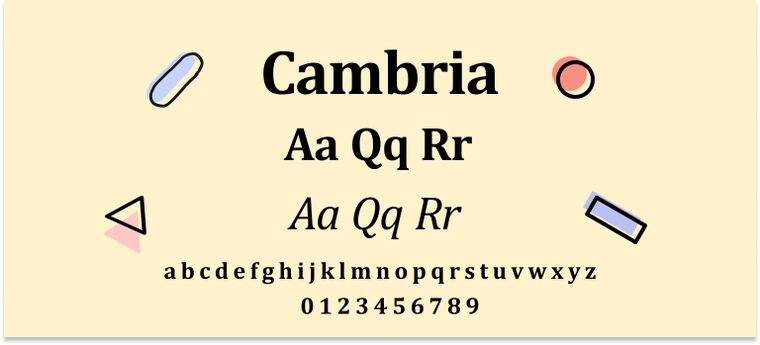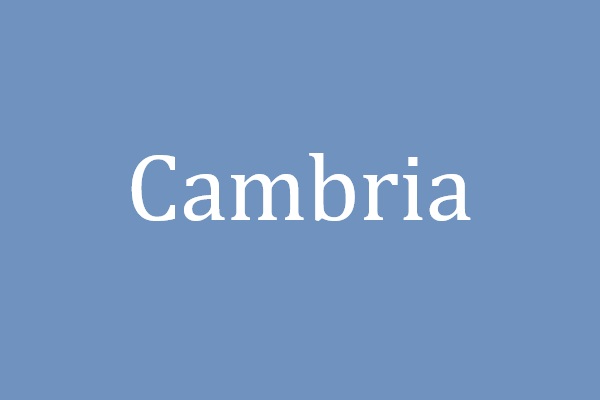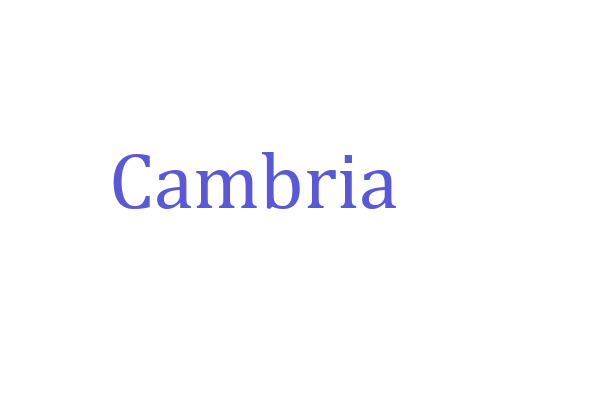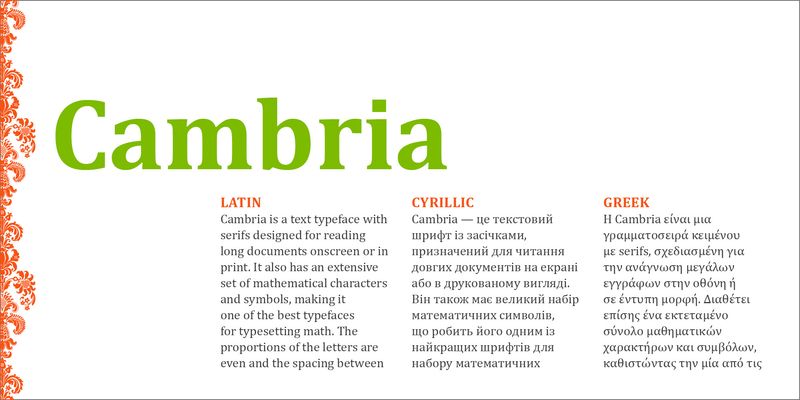
Cambria là bộ phông chữ có chân được thiết kế đặc thù nhằm duy trì khả năng hiển thị rõ nét trên màn hình máy tính và các bản in kỹ thuật. Với cấu trúc chữ vững chãi và độ tương phản vừa phải, việc sử dụng font Cambria Việt hóa mang lại vẻ ngoài trang trọng, tin cậy cho các văn bản thuyết minh dự án hay hợp đồng xây dựng.
Khám phá phong cách thiết kế và độ nhận diện của font Cambria Việt hóa
Nét lôi cuốn đặc trưng của Cambria nằm ở hệ thống chân chữ được thiết kế chắc chắn, giúp định hình dòng văn bản một cách rõ ràng. Khác với các dòng phông chữ có chân cổ điển thường có nét thanh rất mỏng, Cambria duy trì độ dày nét ổn định, giúp văn bản không bị nhòe khi hiển thị ở kích thước nhỏ. Việc tải font Cambria Việt hóa cung cấp một giải pháp xử lý dấu thanh tiếng Việt tinh tế, đảm bảo các ký tự đặc thù như “đ, ă, ơ” luôn cân đối với khung chữ chính, tạo nên nhịp điệu đọc dễ chịu và chuyên nghiệp.
Sự ổn định của bộ phông này còn được đánh giá cao nhờ tính kế thừa từ các chuẩn mực thiết kế hiện đại. Cambria không chỉ toát lên vẻ chính thống của các tài liệu hành chính mà còn mang tư duy thẩm mỹ gọn gàng, phù hợp để trình bày các báo cáo dự toán nhà lắp ghép hay các hồ sơ kỹ thuật chuyên sâu. Đây là phương án hiệu quả để thể hiện sự tận tâm và phong cách làm việc bài bản của đơn vị thiết kế đối với chủ đầu tư và đối tác kinh doanh.
| Phân loại phong cách | Transitional Serif / Business Style |
| Nhóm phông tiêu biểu | Cambria Regular, Bold, Italic, Cambria Math |
| Mục đích phù hợp | Văn bản hợp đồng, Thuyết minh dự án, Công thức toán học |
Gợi ý trình bày: Để bản thiết kế đạt được hiệu quả thị giác cao, bạn nên sử dụng Cambria body font download cho các đoạn văn bản dài để tối ưu trải nghiệm đọc. Trong khi đó, việc kết hợp Cambria bold font download cho các tiêu đề chương sẽ tạo ra sự phân cấp thông tin minh bạch và chuyên nghiệp cho hồ sơ năng lực.
03 Ứng dụng thực tế của phông chữ Cambria trong ngành xây dựng
Nhờ vẻ ngoài khoa học và sự chuẩn mực, việc sử dụng các mẫu chữ từ bộ download font Cambria mang lại giá trị thực tế lớn trong khâu vận hành và quản lý dự án kiến trúc:
- Soạn thảo hợp đồng thi công: Với nét chữ trang trọng, Cambria là lựa chọn ưu tiên cho các văn bản thỏa thuận kinh tế, giấy phép xây dựng nhà lắp ghép, tạo ấn tượng về sự minh bạch và uy tín của doanh nghiệp.
- Trình bày báo cáo dự toán: Các con số và bảng biểu sử dụng Cambria hiển thị rất tách bạch. Đặc biệt, việc sử dụng Cambria math font download giúp các công thức tính toán kết cấu thép hay thông số vật liệu panel trở nên rõ ràng, hạn chế sai sót số liệu.
- Ghi chú trên bản vẽ phối cảnh: Độ sắc sảo của phông chữ này hỗ trợ kiến trúc sư khi trình bày các đoạn mô tả ý tưởng hoặc trích dẫn tiêu chuẩn kỹ thuật trên bản vẽ, giúp khách hàng dễ dàng tiếp nhận thông tin dự án.
03 Lưu ý để bố cục văn bản khoa học với gia đình font Cambria
Để khai thác hiệu quả vẻ đẹp trung tính và công năng của bộ phông đa năng này, người thiết kế nên lưu tâm một số lưu ý kỹ thuật sau:
- Kiểm soát mật độ chữ: Cambria có cấu trúc chữ hơi đậm hơn so với Times New Roman. Bạn nên thiết lập khoảng cách dòng (leading) thoáng hơn một chút để văn bản không bị bết dính nét, giúp hồ sơ dự án trông thanh thoát và dễ đọc hơn.
- Sử dụng biến thể Bold Italic làm điểm nhấn: Khi cần nhấn mạnh các lưu ý đặc biệt hoặc các thuật ngữ chuyên ngành trong hồ sơ báo giá, hãy thực hiện Cambria bold italic font free download để tạo sự khác biệt mà vẫn giữ được tính đồng bộ của bộ chữ.
- Tính tương thích đa nền tảng: Vì Cambria là phông chữ tiêu chuẩn, việc gửi file hồ sơ cho khách hàng qua email sẽ hạn chế được tình trạng lỗi font chữ không mong muốn, giúp đối tác luôn tiếp nhận thông tin một cách trọn vẹn.